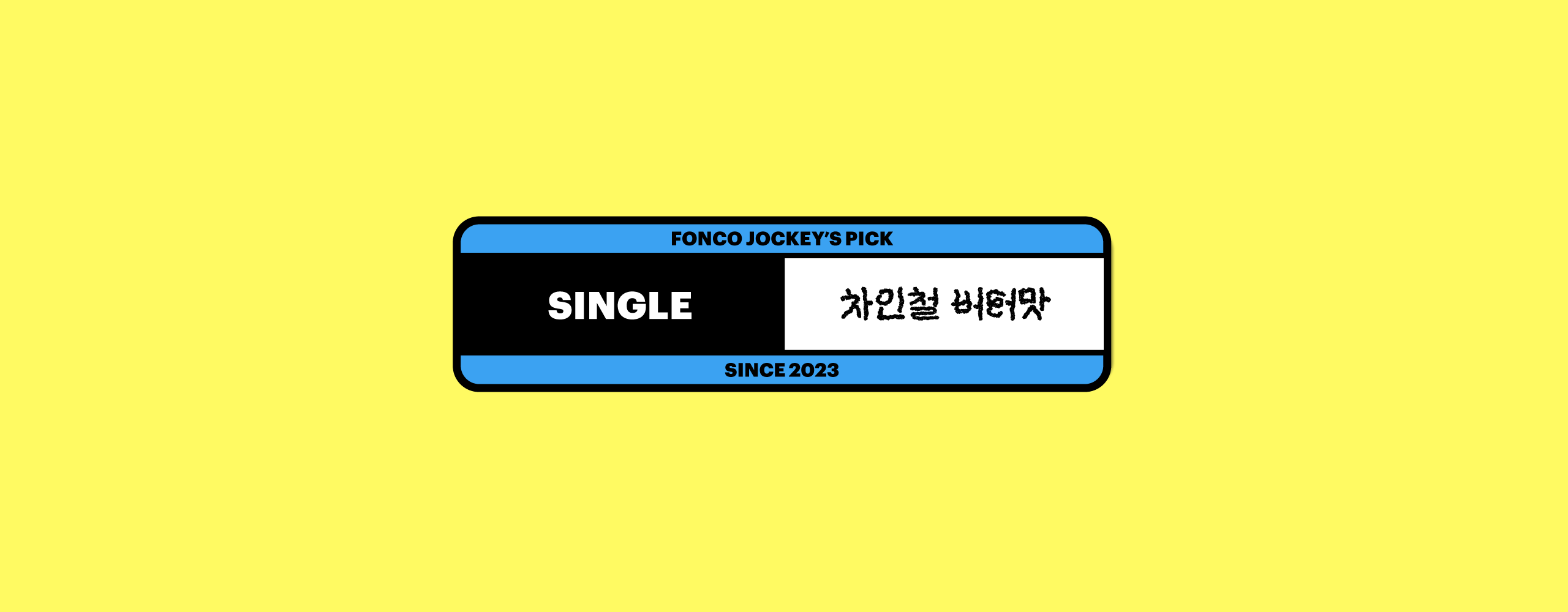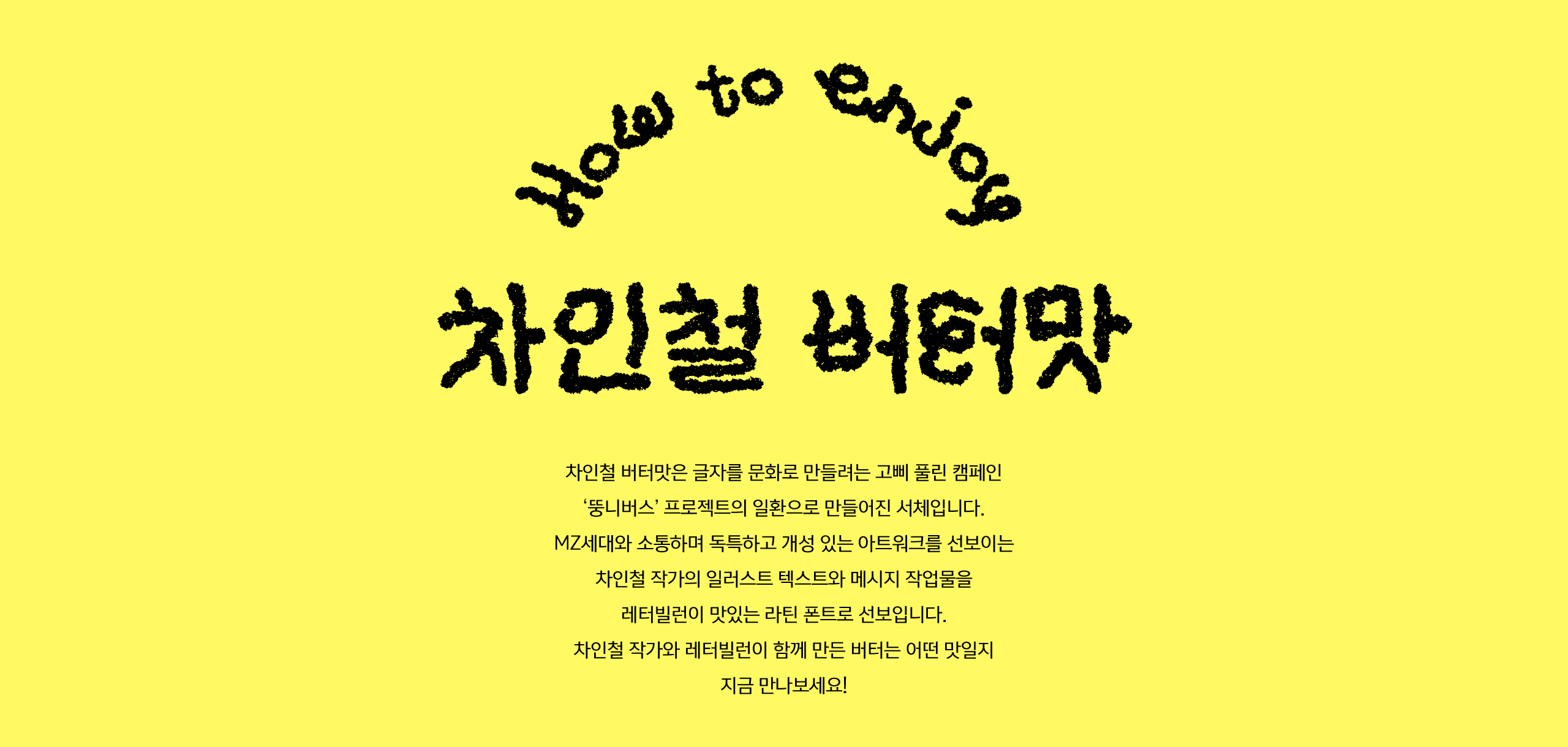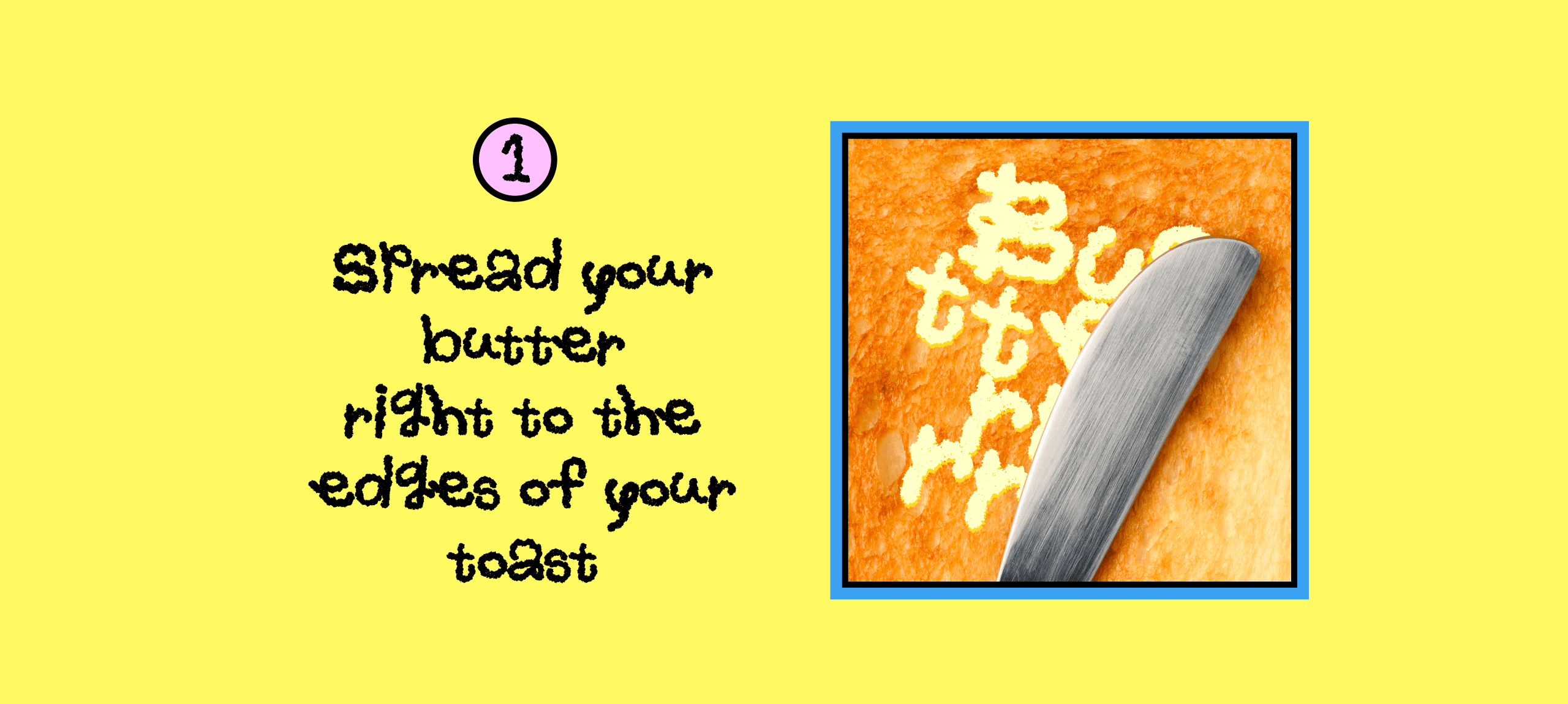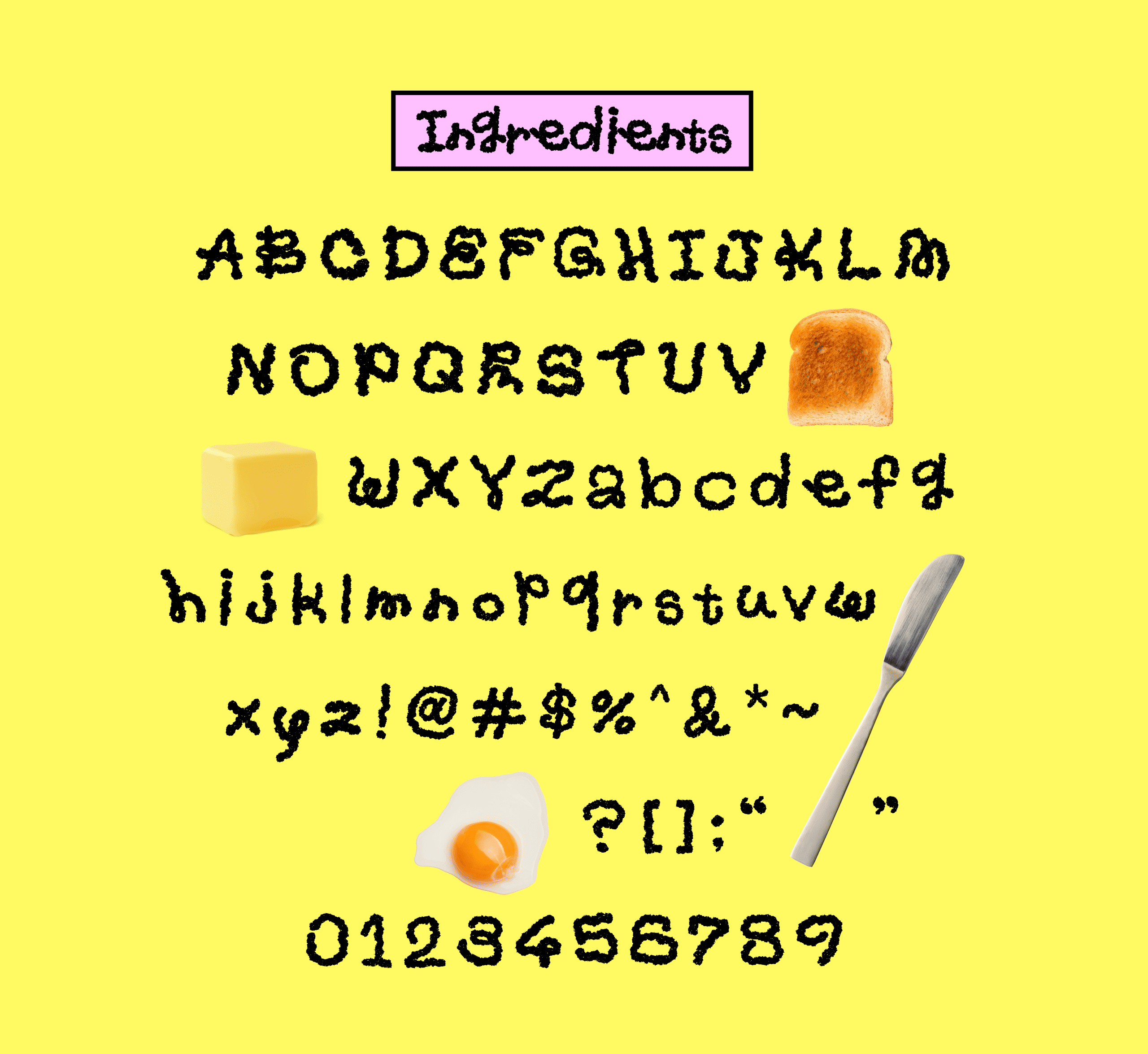
차인철 버터맛
차인철 버터맛은 글자를 문화로 만들려는 고삐 풀린 캠페인 ‘뚱니버스’ 프로젝트의 일환으로 만들어진 서체입니다. MZ세대와 소통하며 독특하고 개성 있는 아트워크를 선보이는 차인철 작가의 일러스트 텍스트와 메시지 작업물을 레터빌런이 맛있는 라틴 폰트로 선보입니다. 차인철 작가와 레터빌런이 함께 만든 버터는 어떤 맛일지 지금 만나보세요!
영문 94자